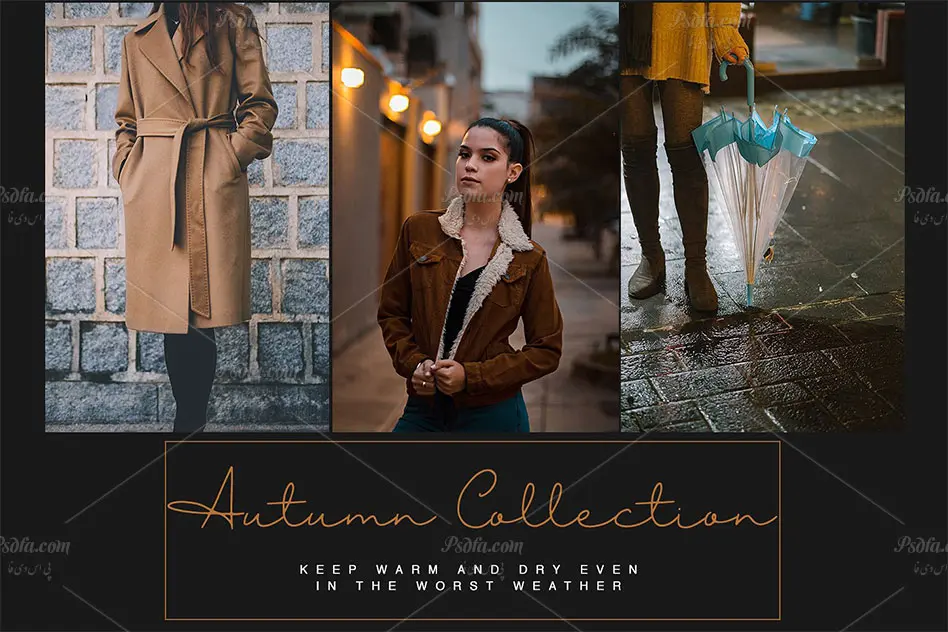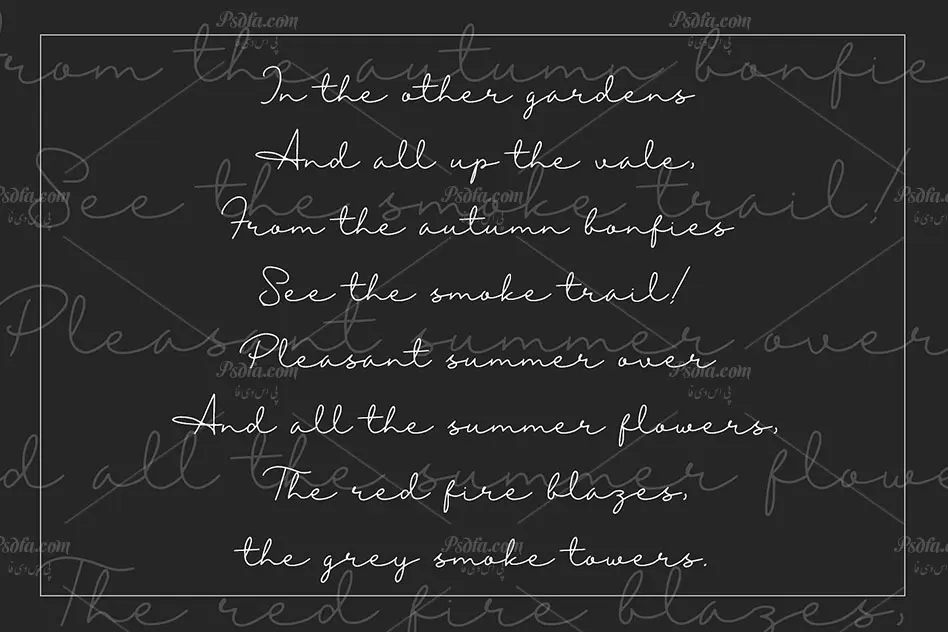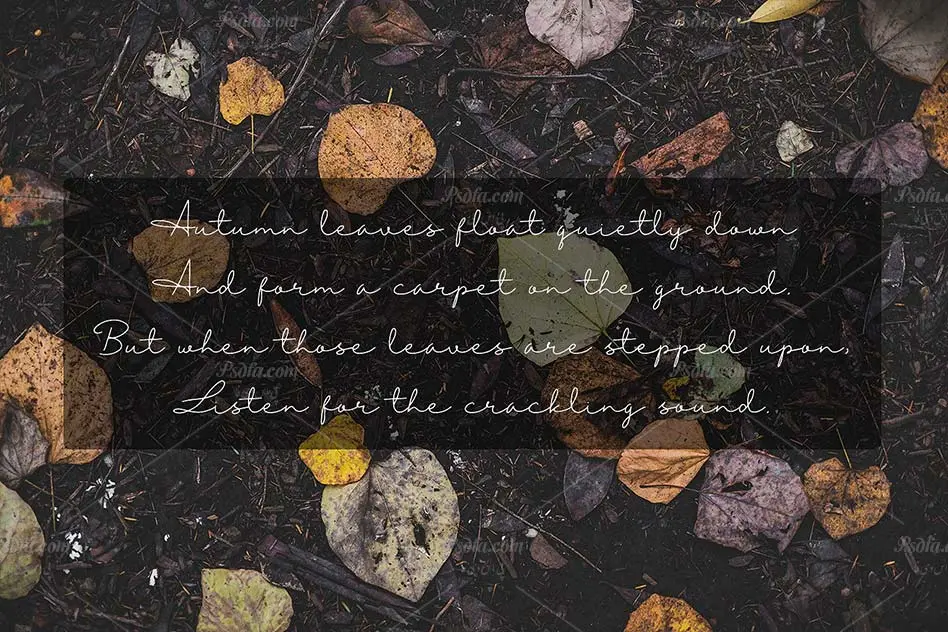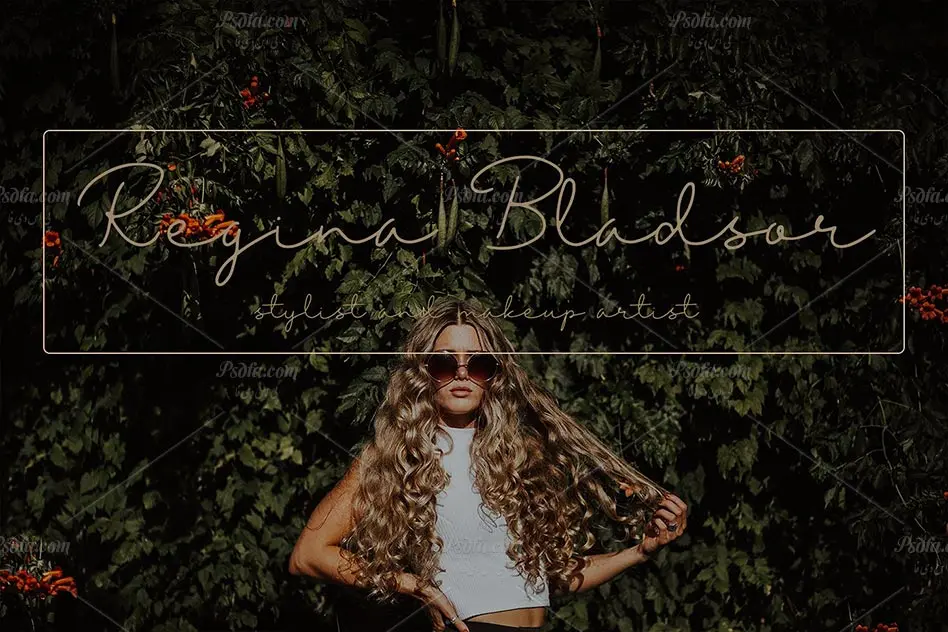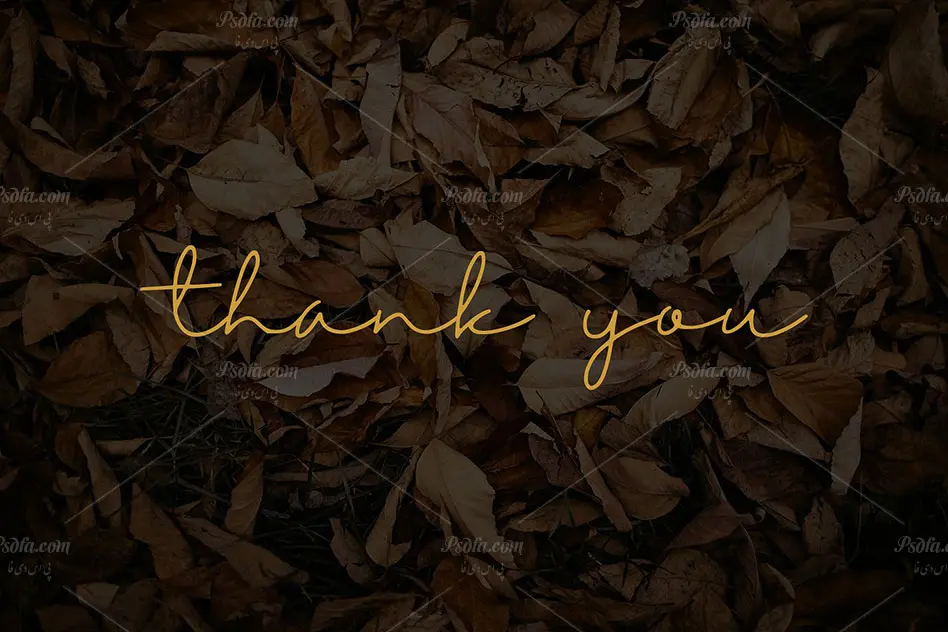
فونت دستنویس انگلیسی Autumn Mood مناسب برای طراحی و گرافیک
فونت دستنویس انگلیسی
در این پست شاهد فونت دستنویس انگلیسی Autumn Mood مناسب جهت استفاده در طراحی و گرافیک می باشید. این فونت زیبا در قالب فایل های ttf , otf , woff و woff2 بر روی سایت بارگذاری شده اند که با نصب یکی از دو فرمت otf یا ttf در پوشه فونت های سیستم قادر به استفاده از آن در تمام نرم افزارهای گرافیکی و ویرایشگر متن از جمله نرم افزار فتوشاپ ، مجموعه نرم افزار آفیس و … خواهید بود. فونت Autumn Mood در وزن معمولی (Regular) طراحی شده است که از آن می توان در طرح های گرافیکی همچون طراحی انواع پوستر ، بنر ، تراکت ، بروشور ، کارت تبریک ، کارت پستال ، کارت عروسی و … استفاده نمود. همچنین از سایر فرمت های این فونت می توان در طراحی صفحات وب نیز استفاده کرد.